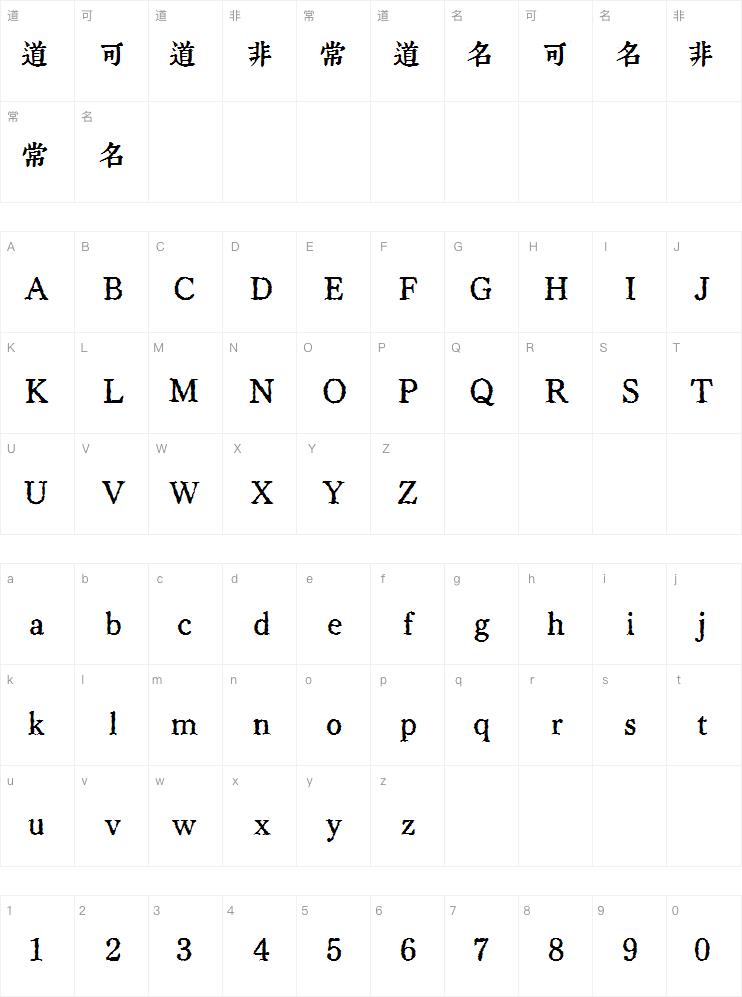
字悦雕版刻宋体” 承继唐宋雕版遗韵,以刀代笔在木梓间复刻汉字千年风骨。其字形恪守方正之本,横画如刀削玉笺般纤劲,竖笔似铁杵入木般劲挺,在规整的布白中暗藏工匠对平衡之美的极致追求。起笔处雕琢出三角饰角,如石刻饕餮纹般庄重,收锋时暗藏刀刻顿挫的古朴肌理,仿佛能听见明代刻坊里凿刀叩木的回响。撇捺如出鞘刃锋,于对称中见凌厉,点画若晨露坠石,在方正间显灵动。此字体将印刷术的实用需求与文人审美熔铸一炉,典雅如宋刻经卷的墨香,清晰似镜鉴文字的魂魄,每一根线条都镌刻着版刻时代的文化密码 —— 横细竖粗的韵律里,是木纤维与刻刀的千年对话;端严平稳的结构中,藏着古人 “天工开物” 的造物哲思,让观者在墨痕刀影间,遇见汉字最本真的庄重与温度。